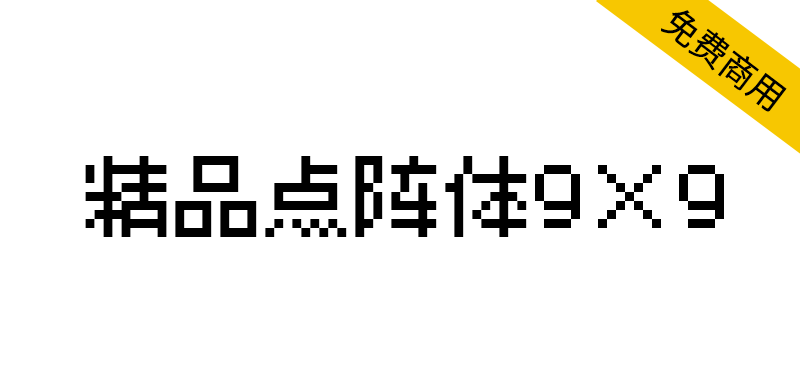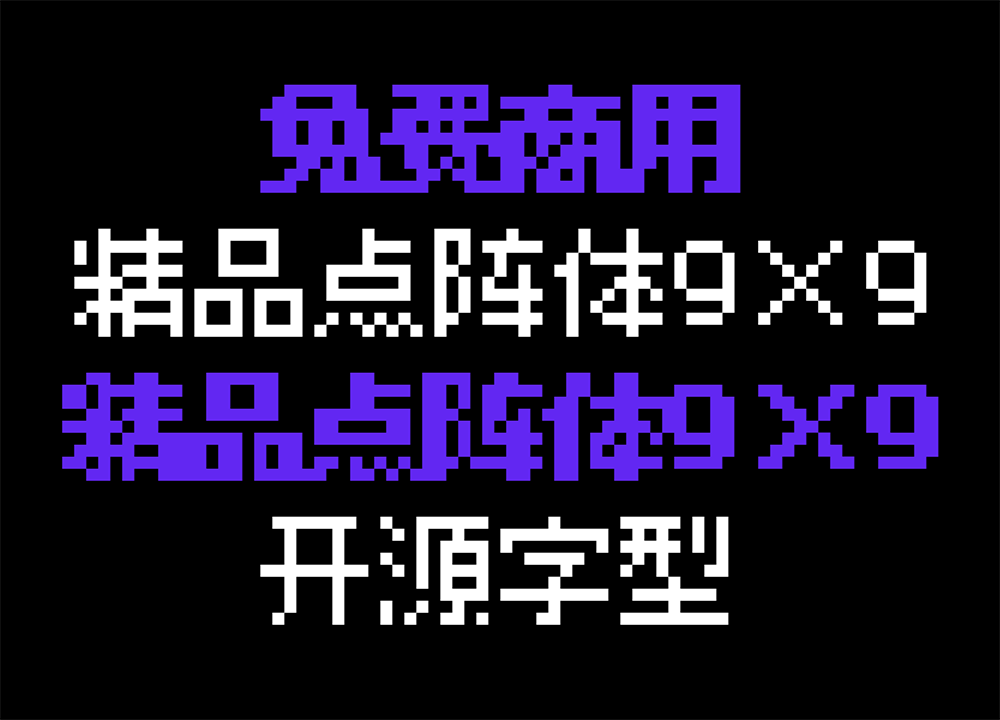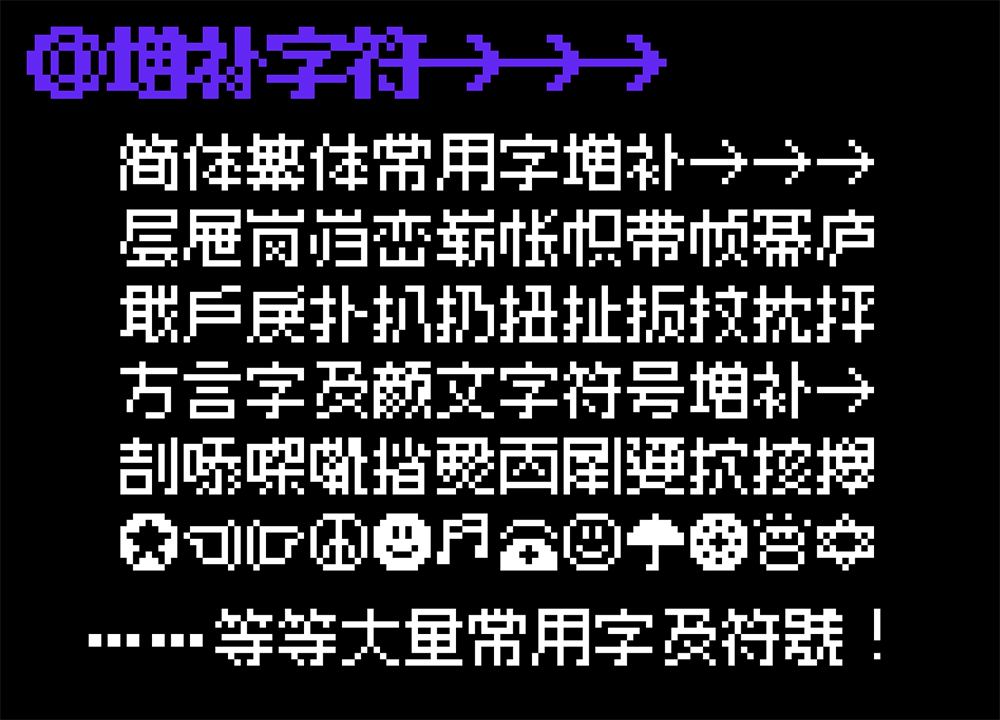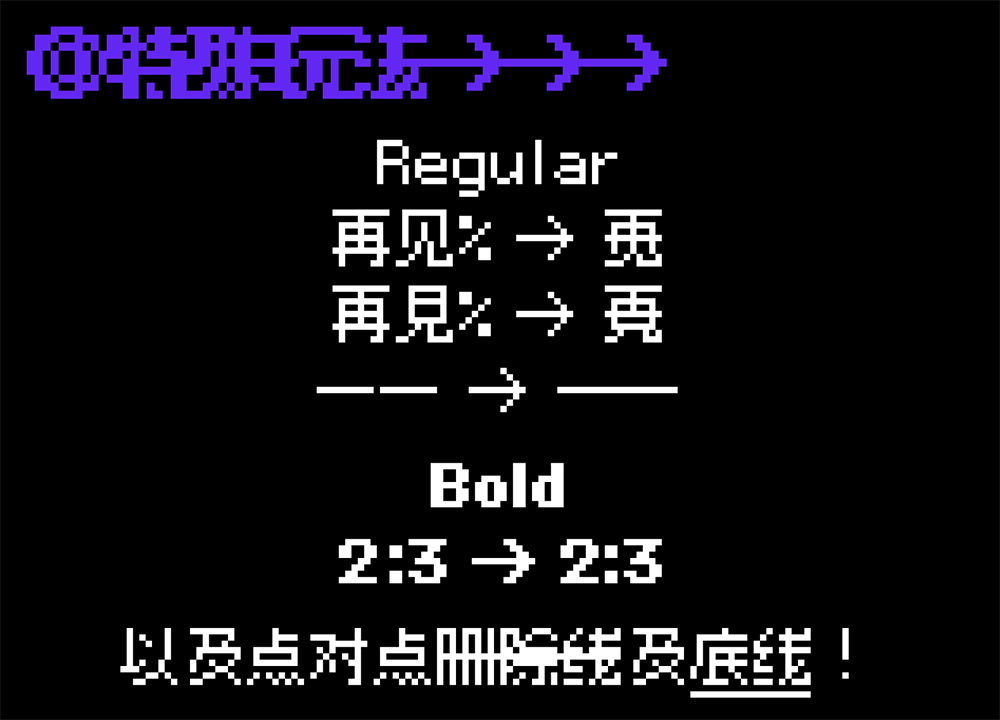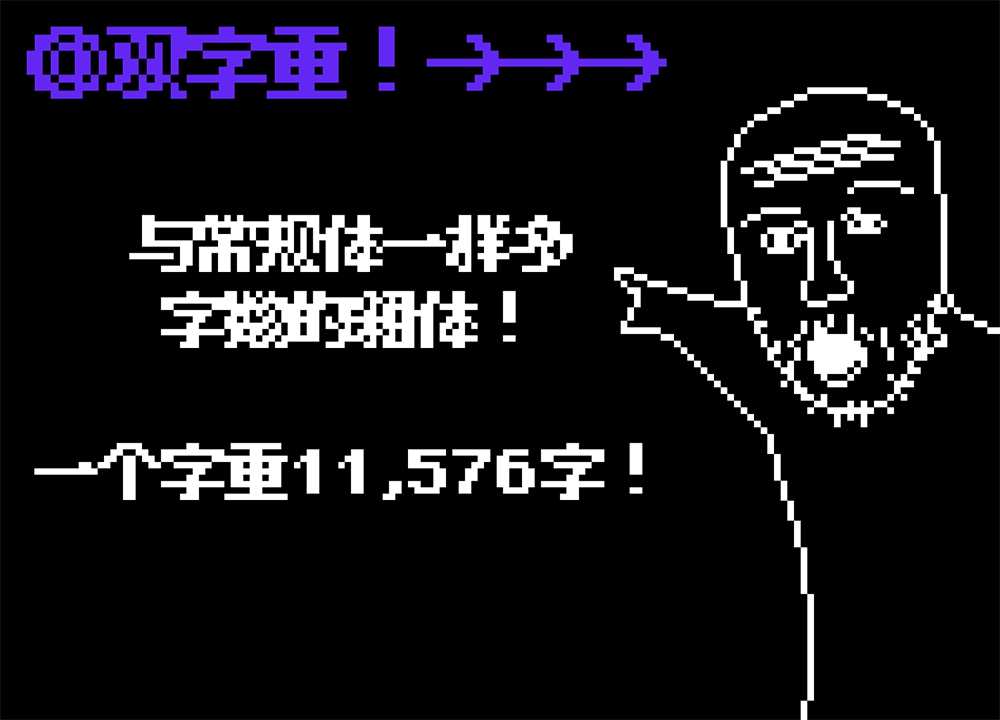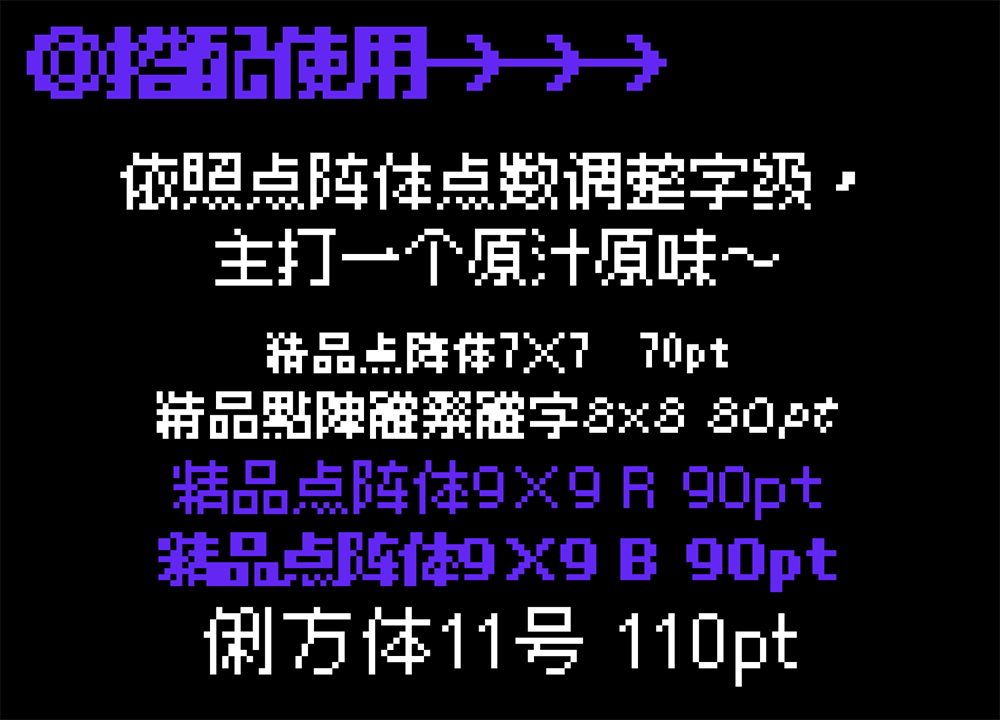
【精品点阵体9×9】非常适合用像素画、游戏主题的点阵字体
精品点阵体9×9 (BoutiqueBitmap9x9))家族是一款基于M+ BITMAP FONTS及ベストテン(BestTen-DOT)改作的字型,目的为适合在繁体中文环境中使用。我们改正了一些标点符号、日本习惯写法、增加大量字符与Opentype特性——包括颜文字用符号、简体中文、直排特性等——使字型使用更方便!这是一款带有极强烈的点阵风格的字型,非常适合用在像素画、游戏相关主题等等。
注意:精品点阵体9×9的常规体与粗体的简体和繁体字符都非常全,但是立体版、光晕版、方格版、圆形版、渐层版的简体字符不是很全,可能会出现缺字,更适合应用于繁体场景。